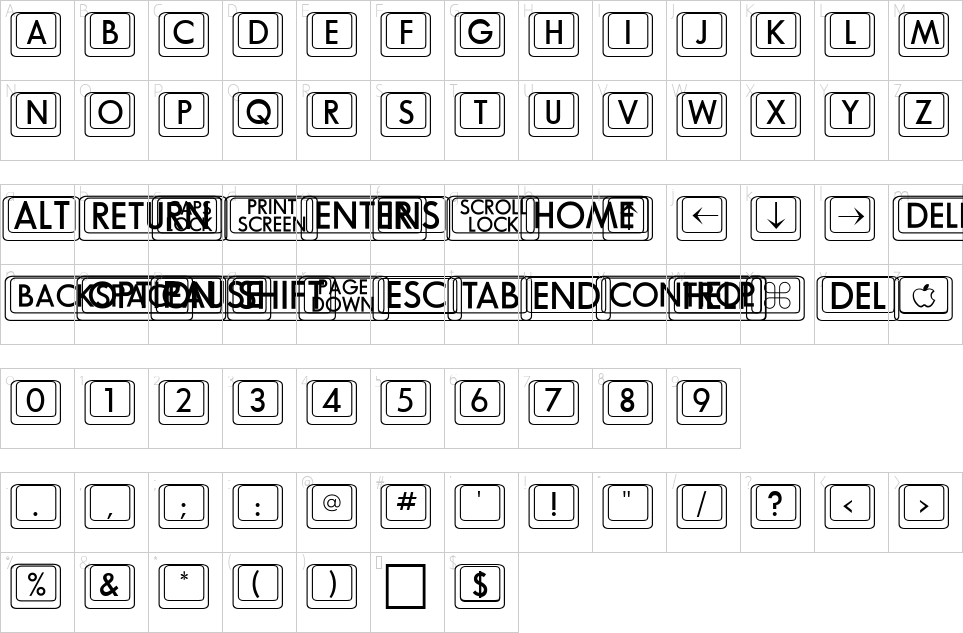
A BK Caps é uma fonte de cap vermelho que surgiu das mãos do designer David Rakowski. Este ícone de estilo único foi projetado para criar texturas vibrantes e chamativas, ideal para destacar mensagens em ambientes digitais variados, desde sites profissionais até logotipos brilhantes. Com uma versão disponível tanto para Windows quanto para Mac, a BK Caps torna-se um recurso indispensável para qualquer criador de designs que busca adicionar um toque atraente e distinto aos seus projetos digitais. Lançada no mercado há algum tempo, a fonte já foi baixada mais de 7 mil vezes, demonstrando seu valor e relevância entre designers e especialistas em design gráfico.